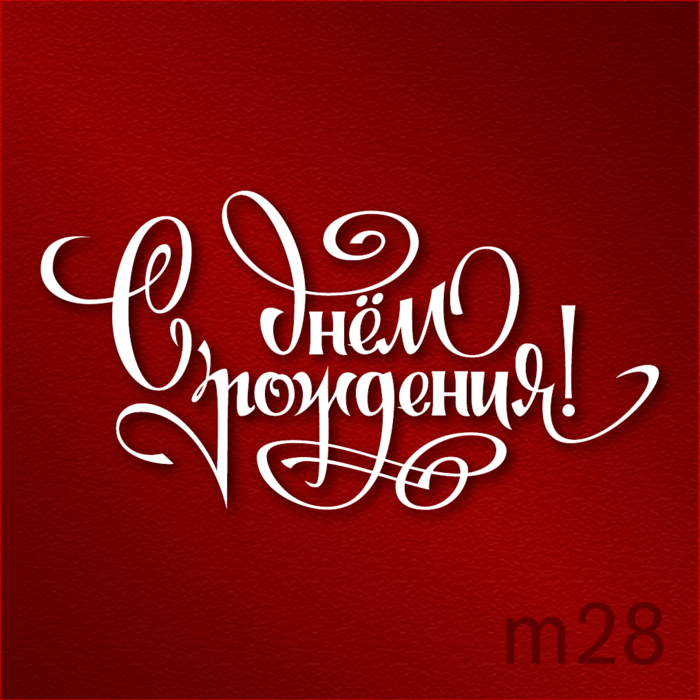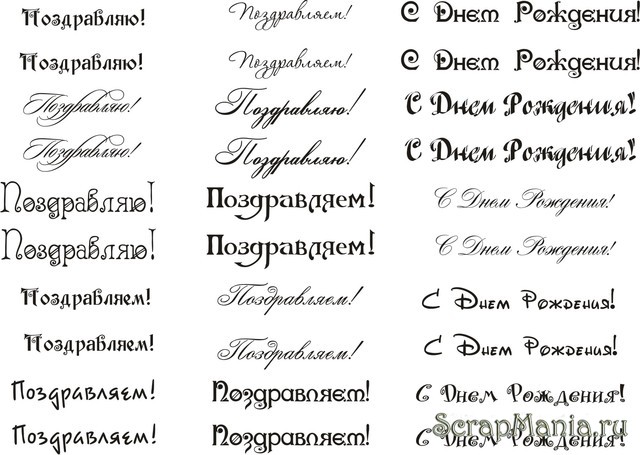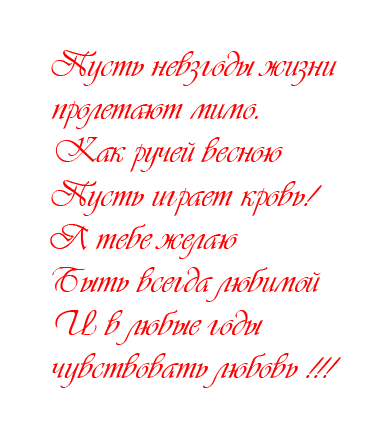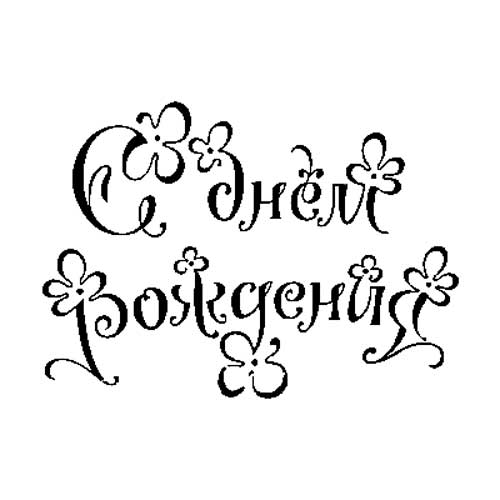
Праздничная надпись с днем рождения
День Рождения – это один из особенных праздников для каждого из нас. Несмотря на то, что мы по-разному воспринимаем этот день, он всё равно остаётся колоритным, не похожим на другие будни. В такой праздник приятно получить красочно оформленные поздравления. В данном материале мы расскажем, как сделать надпись «С Днём Рождения» оригинальным и красивым шрифтом онлайн.
Варианты поздравления с Днем Рождения
Ниже приведём следующие варианты надписей, различных форм и размеров. Выбирайте понравившуюся себе по душе.
Следующая надпись подойдёт при создании поздравления детям, так как включает в себя мультяшного персонажа.
Следующая надпись также подойдёт при создании поздравления ребёнку.
На следующей картинке целый набор надписей, выбирайте для себя понравившуюся:
Как создать свою надпись с красивым шрифтом
Если предложенные альтернативы вас не устроили, тогда можете создать свою надпись «С Днём Рождения». Как с помощью стационарных графических редакторов, так и с помощью специализированных мобильных сервисов, доступных в сети.
Инструкция довольно проста:
- Достаточно будет запустить такой сервис, набрать необходимый текст (поздравительную надпись «Happy Birthday»).
- Затем выбрать оригинальный шрифт, его размер, цвет и другие атрибуты.
- После этого нажмите на кнопку генерации надписи.
Среди сервисов для составления поздравлений стоит отметить следующие:
- online-letters.ru – популярный русскоязычный ресурс для создания красивых надписей «С Днём Рождения». Перейдите на ресурс, выберите красивый фонт для вашей будущей надписи, определитесь с другими атрибутами и сохраните полученный результат;
- flamingtext.com – популярный англоязычный ресурс для создания поздравлений. Перейдите на ресурс, введите требуемый текст и выберите для него красивый шрифт. Для сохранения результата нажмите на «Done» — «Download»;
- cooltext.com – известный в сети ресурс для создания лого и различных надписей. Достаточно перейти на него, выбрать стиль текста, ввести требуемую надпись (например, «Happy Birthday») и нажать на «Create logo».
Создавайте красивые надписи на flamingtext.com
Заключение
В данном материале были представлены ряд надписей «С Днём Рождения», выполненные красивым и необычным шрифтом. А также перечислены ресурсы, позволяющих создать любое поздравление привлекательным фонтом. Используйте предложенные варианты для создания надписей, что станет одной из прекрасных изюминок вашего будущего подарка имениннику.